Лучшие шрифты – 50 крутых бесплатных шрифтов
50 крутых бесплатных шрифтов
Для создания действительно крутых проектов иногда не хватает одной важной детали — хорошего шрифта. В этой подборке вы можете посмотреть и скачать 50 самых популярных шрифтов, которые сделают вашу работу лучше.
Кириллица
Bravo
Yanone Kaffeesatz
BadScript
Nord
Intro Condensed
Ropa Sans
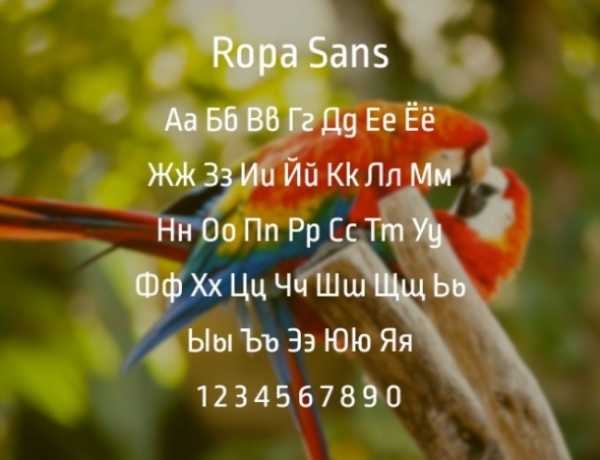
Centar Sans
Lighthaus
Старомосковский
Uni Sans
Clinica Pro
LeHand
Fowviel
Amazing Grotesk
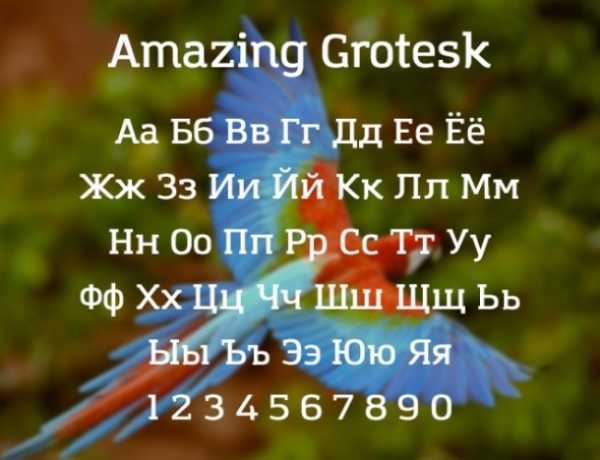
Fira: Firefox OS Typeface
Итоги
Это далеко не единственные варианты бесплатных шрифтов, которые идеально подойдут для разработки или переработки вашего логотипа. Дело в том, что перечислять эти варианты можно бесконечно, и информацию придется укладывать в несколько томов. Теперь вы знаете, какие примеры можно взять за основу, или вовсе использовать их бесплатные варианты. Не забывайте об аспектах выбора, и тогда ваш логотип станет мощным маркетинговым инструментом!